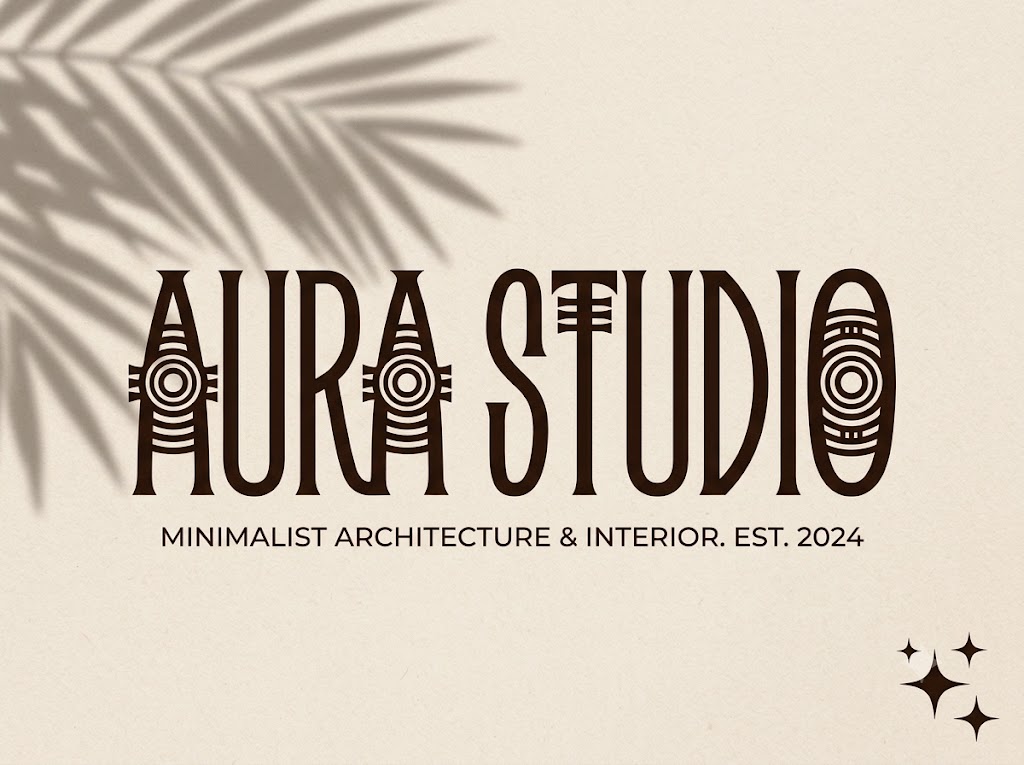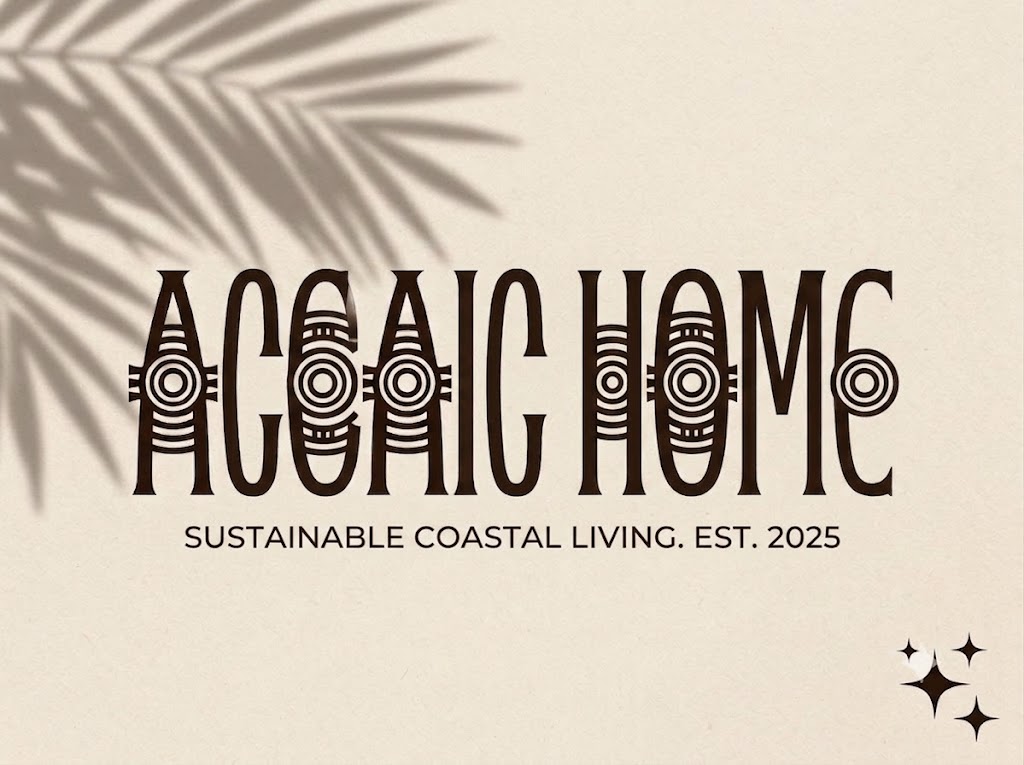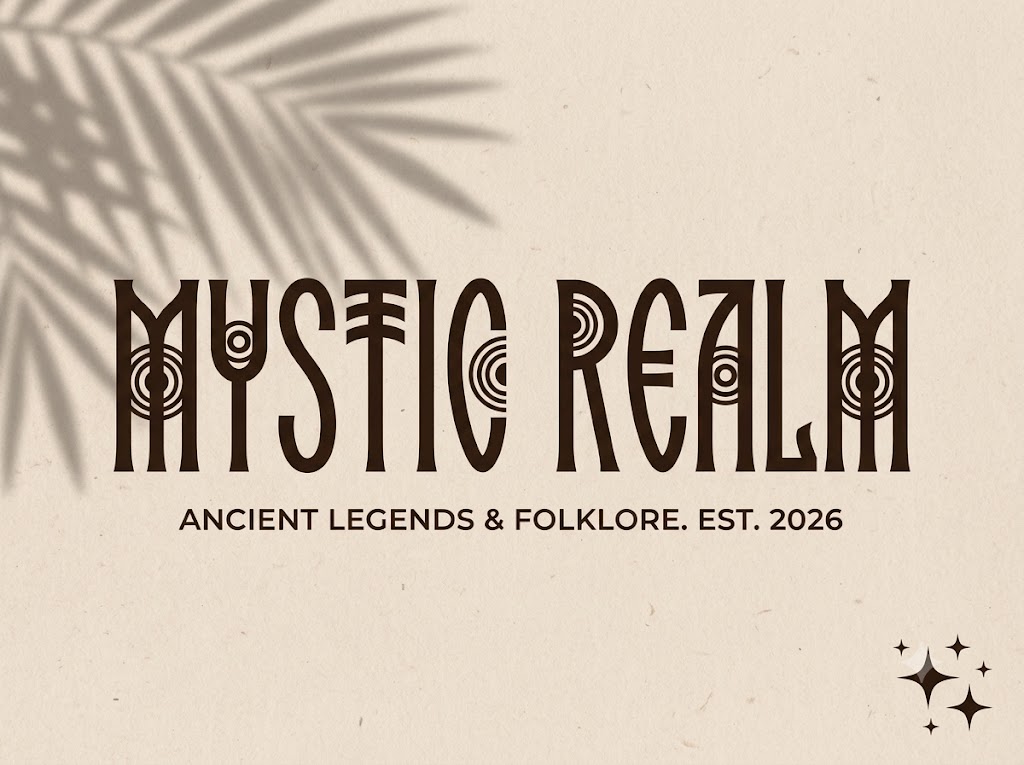
1FTV Methrock
Trong các dự án thiết kế mang tính nghệ thuật cao, phim ảnh giả tưởng, hay ấn phẩm truyền thông cho các thể loại âm nhạc alternative, việc sử dụng các phông chữ phổ thông sẽ làm giảm đi đáng kể sự độc đáo và ma mị của tác phẩm.
Một thiết kế phá cách luôn cần những nét chữ biết nói, mang trong mình chút gai góc, bí ẩn để khơi gợi sự tò mò từ người xem ngay từ cái nhìn đầu tiên.
Nếu bạn đang săn tìm một làn gió mới vừa mang hơi hướng của các ký tự cổ đại, vừa đậm chất rock hiện đại, thì font 1FTV Methrock chính là câu trả lời xuất sắc.
Giới thiệu về font 1FTV Methrock
Font 1FTV Methrock là một bộ chữ hiển thị (display font) vô cùng độc đáo, sở hữu phom dáng cao, thanh mảnh nhưng lại ẩn chứa sự mạnh mẽ và huyền bí.
Sự đồng bộ về mặt kỹ thuật này giúp phông chữ hiển thị cực kỳ sắc nét trên các màn hình độ phân giải cao và giữ nguyên độ mượt mà khi phóng to làm biển hiệu hay poster khổ lớn.
Đặc điểm nổi bật của phong cách thiết kế Methrock
Sức hút khác biệt của font 1FTV Methrock đến từ cấu trúc chữ nén cao (tall & condensed) kết hợp với các ký tự hình học mang tính biểu tượng vô cùng lạ mắt.
Phông chữ được xây dựng theo định dạng All-Caps (hệ thống chữ hoa đồng bộ cho cả hai hàng ký tự), tạo nên sự nhất quán và vững chãi cho các khối văn bản.
Điểm nhấn độc dị nằm ở cách tạo hình các chữ cái như O, B, D, Q, X, S. Đội ngũ thiết kế đã khéo léo lồng ghép các đường gạch ngang, các biểu tượng vòng tròn đồng tâm hay những nét cắt góc cạnh mô phỏng theo các ký tự cổ, chữ rune hoặc các biểu tượng bộ tộc xưa.
Sự kết hợp này mang lại cho Methrock một diện mạo vừa cổ xưa, hoang dại, lại vừa mang tinh thần nổi loạn của dòng nhạc Rock/Metal.
Để phông chữ vận hành mượt mà trên mọi hệ điều hành và phần mềm thiết kế, phiên bản font 1FTV Methrock đã được xử lý kỹ lưỡng về các thông số kỹ thuật nội tại.
Khoảng cách giữa các chữ (kerning) được căn chỉnh cân đối, giúp các biểu tượng độc lạ trên từng ký tự không bị dính vào nhau mà vẫn tạo thành một chuỗi văn bản có tính liên kết cao.
Bên cạnh bộ chữ cái viết hoa đồng bộ, font tích hợp đầy đủ hệ thống chữ số từ 0-9 cùng các ký tự đặc biệt, dấu câu thông dụng (1234567890.,;'"(!?)+-*/=).
Bản Việt hóa chuẩn chỉnh giúp bạn hoàn toàn tự tin sáng tạo các nội dung tiếng Việt có dấu mà không sợ bị lỗi hiển thị hay mất đi phom dáng gốc của chữ.
Hình ảnh demo thực tế của font 1FTV Methrock
Kích thước nhỏ (12pt – 24pt): Các biểu tượng lồng ghép bên trong chữ vẫn được thể hiện rõ nét, không bị nhòe, phù hợp cho các dòng trích dẫn ngắn hoặc sub-headline độc đáo.
Kích thước lớn (36pt – 72pt): Đây là kích thước hoàn hảo nhất để font phô diễn toàn bộ sự ma mị, huyền bí, tạo tác động thị giác mạnh mẽ cho các dòng tiêu đề chính.
Ứng dụng của font Methrock trong thiết kế đồ họa và làm video
Sở hữu nét cá tính độc dị và cấu trúc hình khối mang tính biểu tượng, font 1FTV Methrock mở ra không gian sáng tạo không giới hạn cho các thiết kế phá cách:
Thiết kế Poster phim và bìa truyện: Cực kỳ phù hợp cho các tựa phim thuộc thể loại kinh dị, trinh thám, cổ trang giả tưởng, phép thuật hoặc thần thoại cổ đại.
Bìa album ca nhạc và Merchandise: Lựa chọn hàng đầu cho các ban nhạc rock, indie alternative, hoặc các nghệ sĩ muốn xây dựng hình ảnh ma mị, cá tính trên bìa đĩa và áo thun.
Làm tiêu đề video ngắn (TikTok, Reels, Shorts): Thích hợp cho các video kể chuyện kinh dị, review phim huyền bí, hoặc các nội dung gaming mang phong cách gothic, bộ lạc.
Nhận diện thương hiệu thời trang Streetwear: Phù hợp làm logo, hình in nghệ thuật cho các local brand thời trang đường phố hướng tới sự bụi bặm, nổi loạn và phá cách.